Letras lettering | Letras de lettering
O design de letras lettering é a arte de desenhar caracteres à mão, individualmente, conferindo a cada composição ou letra um estilo único.
É uma técnica muito versátil que permite a criação de vários estilos de desenho à mão livre, como caligrafia falsa, letras góticas ou alfabetos com sombras e outros elementos.
O lettering é amplamente utilizado por designers gráficos, ilustradores e criadores de conteúdo em projetos de identidade visual e branding, pois ajuda a humanizar as marcas.
Além disso, é uma técnica popular entre entusiastas de artesanato e outros profissionais, especialmente nos setores de hotelaria, comércio local e planejamento de eventos. Nesses contextos, quadros de giz comerciais e sinalização decorativa são elementos essenciais para atrair clientes.
O lettering mais famoso no Brasil são as frases de para-choques de caminhões, que são características, bem-humoradas ou reflexivas, e que mantêm a arte do lettering viva na cultura brasileira.
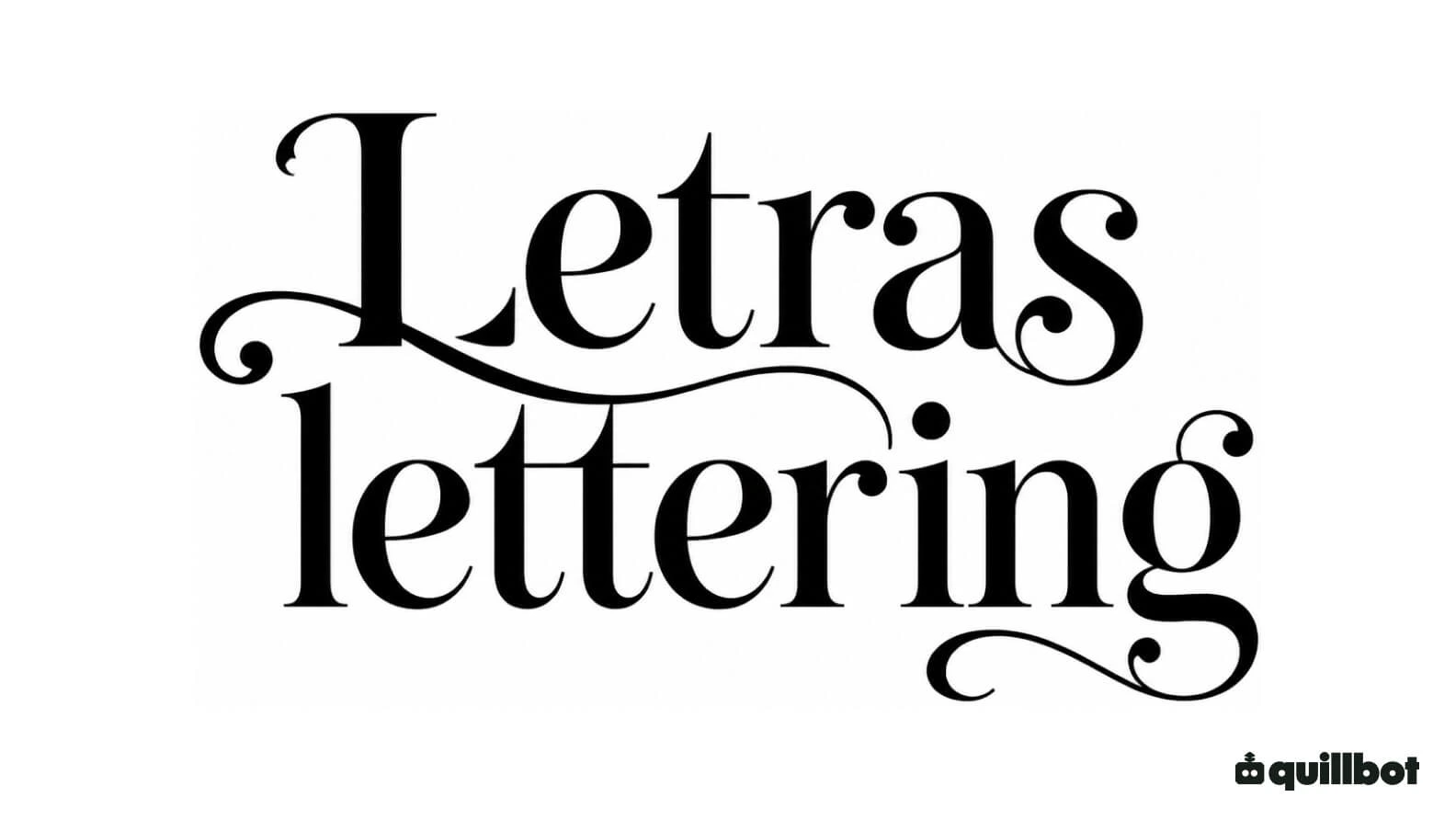
O lettering é a arte de desenhar letras à mão de forma personalizada para criar palavras, frases ou composições visuais. Cada letra é concebida como uma ilustração.
A caligrafia é a arte de escrever letras à mão usando traços contínuos e controlados, com o auxílio de instrumentos como penas, marcadores ou pincéis. Ela se concentra na beleza, expressividade e técnica da escrita manual.
Tipografia é a disciplina que se ocupa do design e da organização de tipos de letra e seus caracteres (letras, números e símbolos) para facilitar a leitura e a comunicação visual. Pode ser digital, mecânica ou mesmo física (como letras esculpidas ou escritas à mão).
Principais pontos
- O lettering é a arte de desenhar letras à mão, criando composições personalizadas que se diferenciam da caligrafia e da tipografia e são amplamente usadas em design, branding, artesanato e comunicação visual.
- Dominar os traços básicos, utilizar as ferramentas adequadas e praticar grupos de letras são os primeiros passos para desenvolver um lettering harmonioso e profissional.
- Existem diversos estilos de lettering, como brush lettering, bounce lettering, chalk lettering, hand lettering e faux calligraphy, cada um com características e aplicações específicas.
- O lettering é uma técnica versátil que permite criar desde placas comerciais e embalagens até convites, presentes personalizados e as tradicionais frases em para-choques de caminhões, um dos exemplos mais icônicos dessa arte no Brasil.
Letras lettering bonitas
Um belo design de letras lettering se baseia em dois pilares fundamentais:
Traços básicos para letras lettering
Antes de começar a desenhar letras, é importante praticar os traços básicos. Esses exercícios ajudam a desenvolver o controle da pressão e a melhorar a precisão dos seus movimentos.
Alguns dos traços básicos para criar letras são:
- Linha fina ascendente: um traço feito de baixo para cima com pressão mínima. A caneta deve apenas tocar levemente o papel para obter uma linha fina e uniforme.
- Linha grossa descendente: um traço de cima para baixo, aplicando pressão firme no papel. Isso permite que a ponta do marcador ou as fibras do pincel se flexionem e criem uma linha larga.
- Oval: uma forma que começa à direita (às 2 horas em um relógio). Ela desce à esquerda com um traço grosso (com pressão) e sobe à direita com um traço fino (sem pressão) até completar a forma.
- Arco: uma curva semelhante à forma de um “n”. Um traço fino é feito ao subir para a esquerda; ao atingir o topo, aplica-se pressão durante a curva e um traço grosso é continuado ao descer para a direita.
- Curva em U: um traço semelhante à letra “u”. Ele desce para a esquerda com um traço grosso, diminuindo gradualmente a pressão à medida que se aproxima da base, e sobe para a direita com um traço fino.
- Onda contínua: um traço composto que combina o arco e a curva em U. Começa com uma linha fina, aumenta a pressão à medida que se move para baixo e diminui até terminar com uma linha fina.
- Laço ascendente: ascende da esquerda com um traço fino, forma um laço no topo e desce em linha reta, aplicando pressão para criar um traço grosso. É um traço comum em letras como “b”, “d”, “h” e “l”.
- Laço descendente: o traço é desenhado para baixo no lado esquerdo com pressão para criar um traço grosso e, em seguida, suavemente para cima no lado direito para criar um traço fino. Isso é característico de letras como “g”, “j” ou “y”.
O círculo cromático permite criar combinações harmoniosas e atraentes através da utilização de cores secundárias, como o verde, o laranja e o roxo, que conferem dinamismo e frescor aos designs.
Para obter um contraste que chame a atenção, a chave é combinar cores complementares, ou seja, aquelas que estão em posições opostas no círculo cromático, como vermelho e verde, amarelo e violeta ou azul e laranja.
Tipografia é uma palavra que vem do latim renascentista, typographia. Typos (τύπος) vem da língua grega e significa “impressão” e -graphia (-γραφία), também do grego, quer dizer “escrita”.
Literalmente, o significado original da palavra tipografia era “impressão de escrita”, contrastando com o manuscrito.
Atualmente, tipografia refere-se à arte ou técnica de organizar textos e letras de maneira clara e agradável.